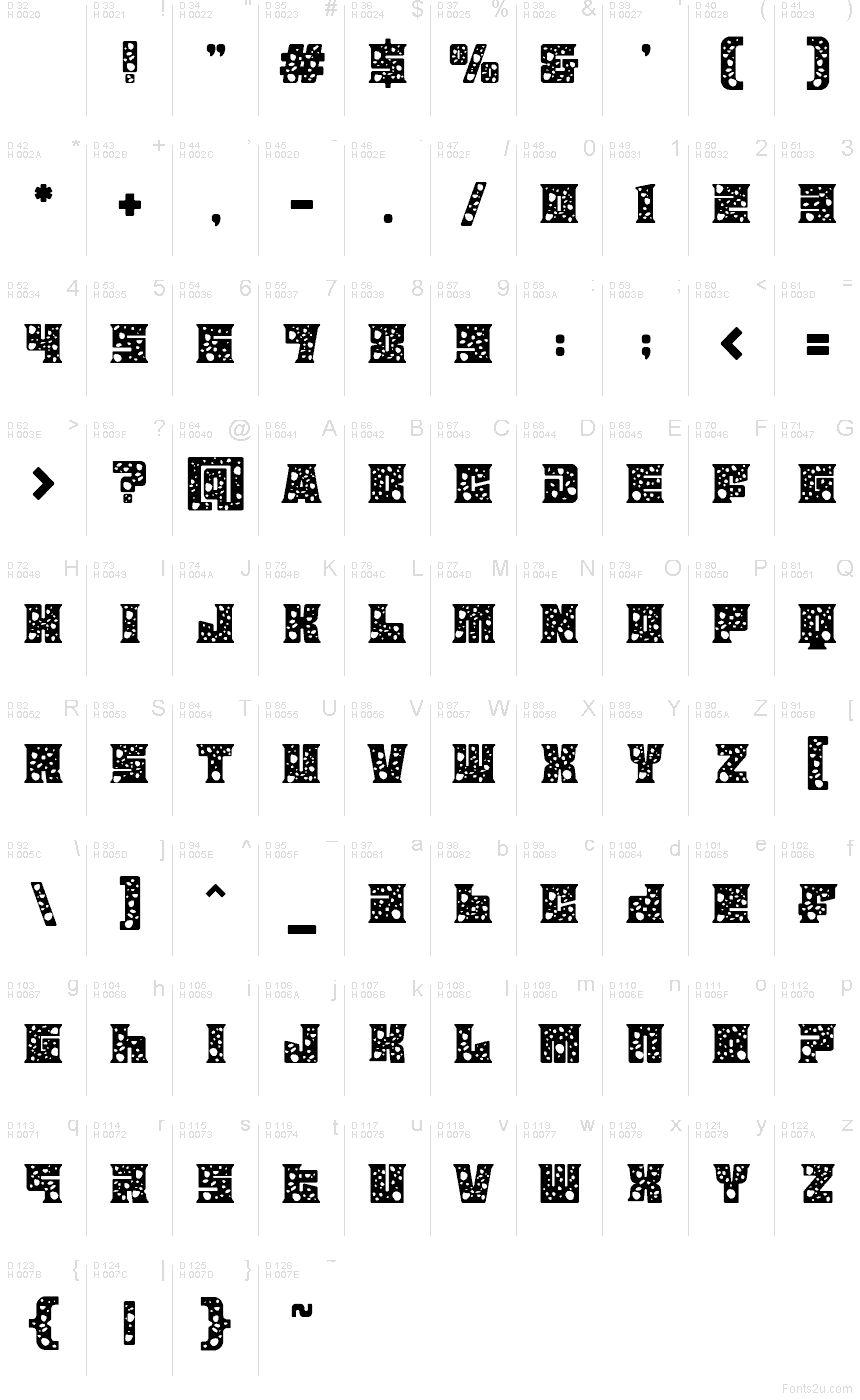
Astral Zenith Nine od Putracetol Studio je bezplatné písmo typu display ve vesmírném stylu, tvořené temnými geometrickými tvary s otvory připomínajícími kamínky. Tato opakující se hvězdná textura dodává písmenům kráterový, kosmický vzhled, zatímco hranatá silueta udržuje graficky přesný design, který nepůsobí jako ruční kresba.
Nejlépe vynikne v sci-fi titulcích, grafice her, plakátech, náhledech videí na YouTube a tematickém zboží, kde kropenatý vnitřek sám o sobě vytváří atmosféru. Krátké nadpisy a loga těží z kombinace pevné struktury a roztroušených nebeských výřezů, což každému slovu dodává silný tematický náboj bez nutnosti dalších ilustrací.
Astral Zenith Nine